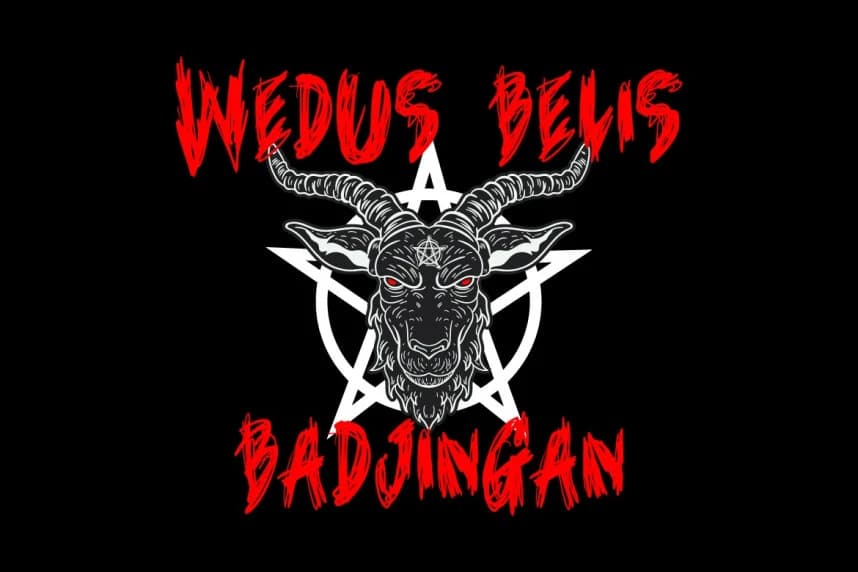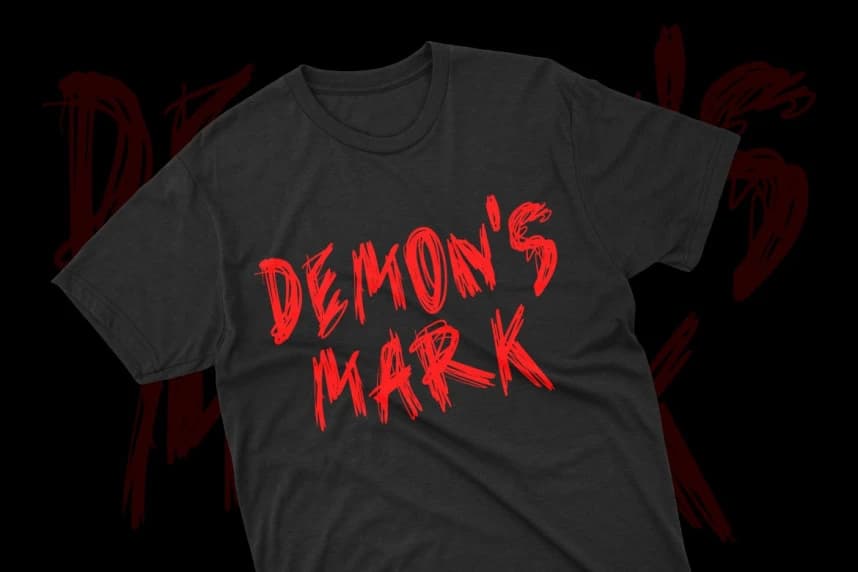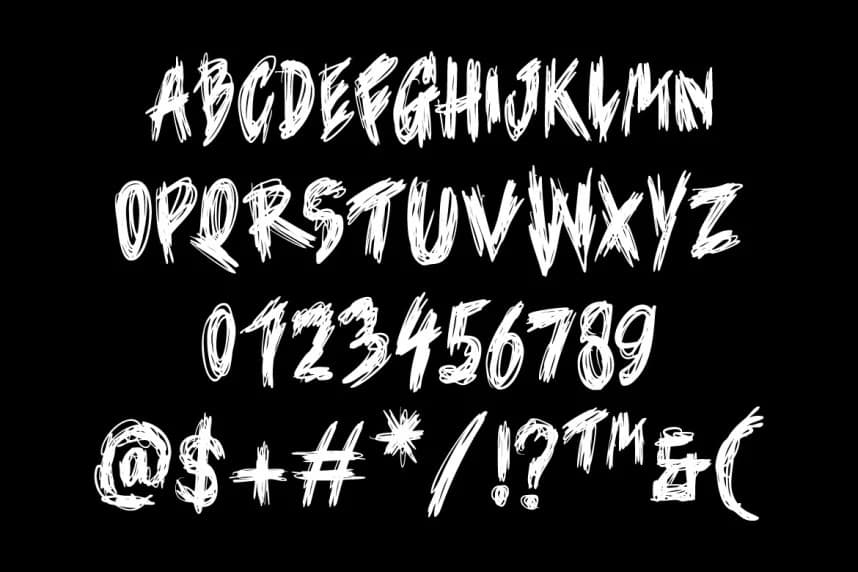
Trash Secret Font
Trash Secret Font, yaratıcılığın vahşi bir ifadesidir; titizlikle elle çizilmiş, kalemle karalanmış kaotik bir tarzda. İsyankar sanatın somutlaşmış hâli olup, geniş bir tasarım uygulamaları yelpazesi için idealdir.
Trash Secret Font, yaratıcılığın vahşi bir ifadesi olup titizlikle elle çizilmiş, karalayıcı ve kaotik bir stilde tasarlanmıştır. Asi bir sanat anlayışının somutlaşmış hâli olan bu yazı tipi, geniş bir tasarım uygulama yelpazesi için idealdir.